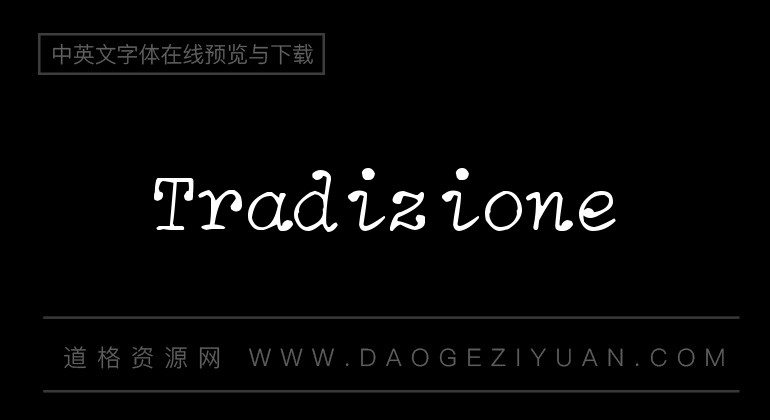
Tradizione 是一款由意大利设计师 Massimo Vignelli 设计的文字字体。它是一种经典的衬线字体,具有简洁、流畅的线条,具有细腻的细节,拥有优雅的外观。它的设计灵感来源于意大利的传统文字,以及意大利的文化和历史。它具有清晰的结构,可以用于各种用途,包括书籍、杂志、海报、标志等。内容介绍
Tradizione是一款非常不错的手写艺术字体,具有很好的视觉感,适合于文化类的宣传设计、商业类品牌的广告和产品包装设计以及个性化文字排版等较多场景。